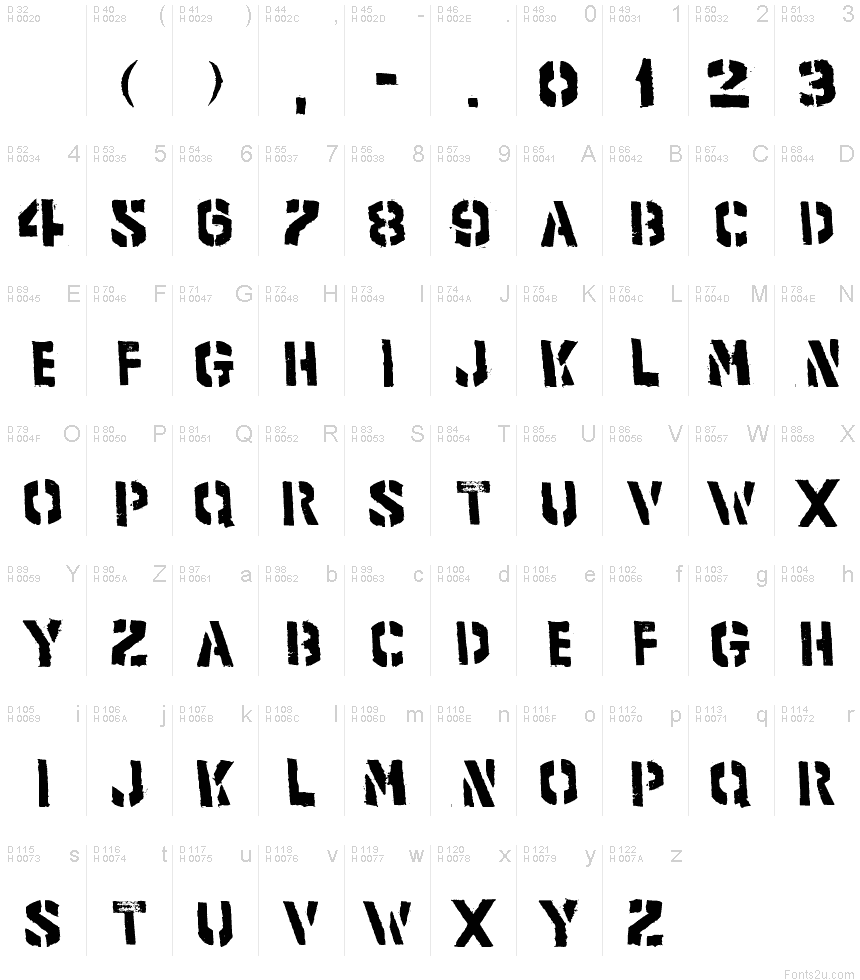
Product von Stefab Claudius und Schmusy für Phantomphonts ist eine kostenlose Display-Schrift mit rauem Industrial-Charakter. Die Buchstaben sehen aus, als wären sie aus verbeultem Blech geschnitten, mit blockartigen Silhouetten, zerkratzten Kanten und rauen Lücken, die sich durch die Großbuchstaben ziehen und dem Alphabet einen abgenutzten, gestempelten, fast postapokalyptischen Rhythmus verleihen.
Sie eignet sich für Plakate, Albumcover, Spieletitel, Zines und gritty Branding, wo eine kostenlose Schrift eher markant als glatt wirken soll. Verwenden Sie sie für kurze Überschriften, Logo-Skizzen oder einzeilige Titel, denn die schweren rechteckigen Formen und die zerbrochene Textur erledigen den Job im Handumdrehen.